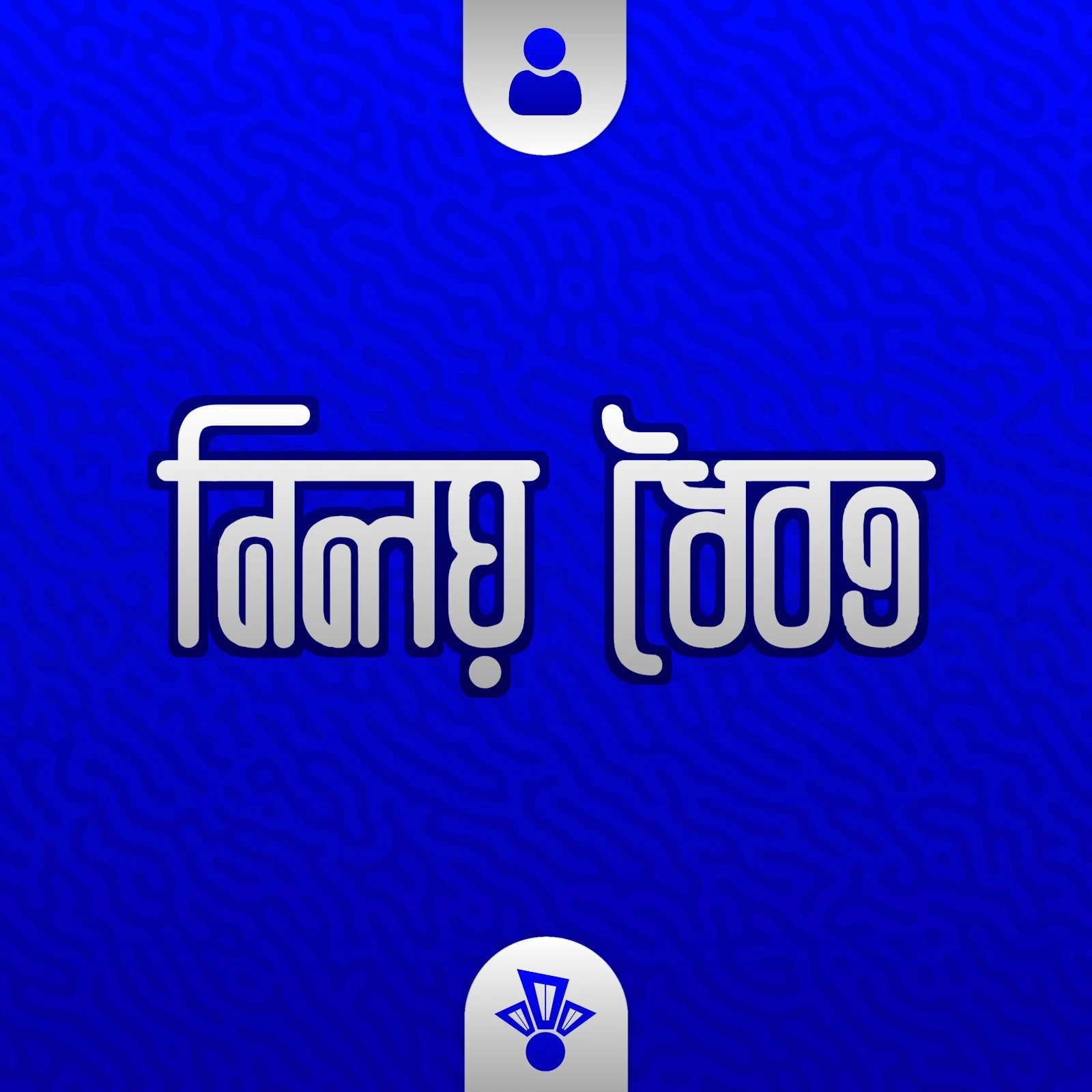
নিলয় ধৈবত একটি ইউনিক প্যারাগ্রাফ বাংলা ফন্ট। যেকোনো ধরণের বাংলা ডিজাইনের কাজে ফন্টটি অত্যান্ত উপযোগী। বাংলা সংগীতের ষষ্ঠ মৌলিক সুর ধা এর পূর্ণরূপ ধৈবত শব্দটা থেকে ফন্টটির নামকরণ করা হয়েছে।
নিলয় ধৈবত
- নকশাকার : আরিফিন রহমান নিলয়
- বিকাশকারী : মোহাম্মদ আদেল
- ধরণ : ইউনিকোড
- রূপ : ৪ টি
- বর্ণের ভাষা : বাংলা